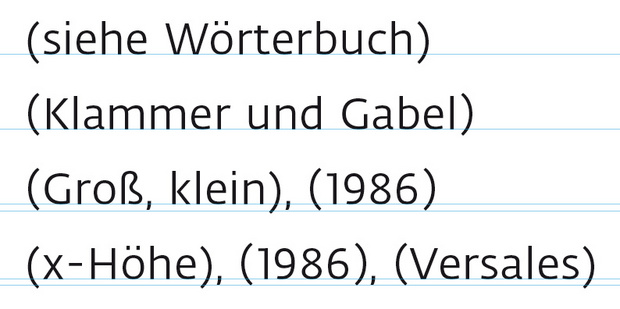
Case Sensitive Klammern bei gemischten Schreibweisen?
beim Setzen eines Textes mit vielen geklammerten Texteinschüben stehe ich vor diesem Problem: case sensitive Klammern bei Versalien zu verwenden ist ein nettes Feature, wenn die Schrift über entsprechende Klammern verfügt, die ihre Form nicht ändern, sondern nur nach oben rutschen (z.B. Fedra Sans). Aber wie setze ich, wenn in kurzen Abständen oder innerhalb einer Klammer gemischte Schreibweisen vorkommen (Zeile 3 und 4, s. Abb.)? Ich tendiere momentan dazu, alle Klammern als Versal-Klammern zu behandeln, wenn sie direkt nebeneinander vorkommen.
Für meine Augen stehen z.B. bei der »(x-Höhe)« die Klammern sowieso optisch etwas zu tief. In diesem Sinn würde ich Dir beistimmen und vermutlich konsequent die Versal-Variante verwenden.
Das ist aber nur meine ganz unprofessionelle Meinung.
Im Bleisatz gibt es nur eine Art Klammer im Setzkasten. Mir ist schon gelegentlich aufgefallen, daß die Klammern mancher Schriften ungünstiger sitzen als andere, aber verändern kann man das in einem Brotschriftgrad nicht, deshalb ist mir diese Problemlösung neu. Wenn du dich im digitalen Satz um dieses Detail kümmerst, korrigiert du dann in einem Text jedes Klammerpaar einzeln? Ist ein solcher Aufwand gerechtfertigt? Bei einem klammerreichen Text steigt doch der Preis für diese Feinkorrektur merklich an, oder?
Bei langen Fließtexten korrigieren ich das nicht, aber bei Briefbögen und Visitenkarten verschiebe ich die Klammern schon einen Hauch nach oben wenn sie zu tief hängen. Das sieht sonst einfach falsch aus, besonders, weil bei Telefon- und Faxnummern nur eine Null in den Klammern steht, die sofort verrät, wenn die Klammern nicht gut sitzen.
Im Bleisatz gibt es nur eine Art Klammer im Setzkasten. Mir ist schon gelegentlich aufgefallen, daß die Klammern mancher Schriften ungünstiger sitzen als andere, aber verändern kann man das in einem Brotschriftgrad nicht, deshalb ist mir diese Problemlösung neu. Wenn du dich im digitalen Satz um dieses Detail kümmerst, korrigiert du dann in einem Text jedes Klammerpaar einzeln? Ist ein solcher Aufwand gerechtfertigt? Bei einem klammerreichen Text steigt doch der Preis für diese Feinkorrektur merklich an, oder?
Dieses Feintuning hängt erst mal von der Schrift ab. Wenn das Verschieben der Klammern einen besseren Satz ergibt, dann macht es bei überschaubaren Text für mich Sinn. Den Aufwand kann man relativ in Grenzen halten, indem man für Klammern ein Zeichenstilvorlage erstellt und dann per Suchen und Ersetzen alle Klammern mit dieser Case Sensitive Funktion belegt. Dann wäre es eine einheitliche Lösung. Daher auch meine Frage, ob man „normale“ oder „höher gestellte“ Klammern mischen kann? Ich finde es eigentlich wichtiger, etwas Luft zwischen dem folgenden oder vorherigen Zeichen und der Klammer zu geben, wenn es zu eng zugeht.
Mich stört es, wenn nebeneinanderstehende Klammern verschiedene Höhen haben. Ich würde im Fließtext einheitlich etwas nach oben gerückte Klammern verwenden; da Oberlängen wesentlich häufiger sind als Unterlängen, wirkt es so auch bei Kleinbuchstaben m.M.n. ausgeglichener.
Ich finde es eigentlich wichtiger, etwas Luft zwischen dem folgenden oder vorherigen Zeichen und der Klammer zu geben, wenn es zu eng zugeht.
Das hat mit der Höhe der Klammern nichts zu tun. Die Schrift sollte so zugerichtet sein, daß die Klammer etwas Fleisch hat. Im Bleisatz habe ich noch nie am Wort klebende Klammern spationieren müssen. (Und das sagt ein denkbar penibler Setzer, der noch mit Seidenpapier in Petit-Schriften ausgleicht, wenn es nötig erscheint.)
Eine unterschiedliche Klammerhöhe darf im Text nicht sichtbar werden, so wären nebeneinanderstehende Klammerpaare in gleicher Höhe zu setzen. Das heißt auch, daß mit Suchen und Ersetzen in einem Werksatz nichts gewonnen ist, weil man den gesamten Text nach jeder Korrektur durchsehen müßte, ob dieses Problem auftritt. Kann man auch mit der Suchfunktion machen, ist aber in meinen Augen überflüssige Liebesmüh, wenn die Schrift selbst eine halbwegs anständige und gut zugerichtete ist. Da stören kleine Akzente den Lesefluß nicht.
Entscheidend ist nicht das Detail in der Regel-Anwendung, sondern der Entwurf nach den weniger genau definierten Regeln der Kunst. Es gibt wenige Autoren, die das einräumen. Man kann es bei Paul Renner lesen: der Satzspiegel sei zwar berechenbar, aber wie er seitlich letztlich auf der Seite steht, kann man nur in einem aufgeschlagenen Blindband festlegen, also nicht allein geometrisch. Auch wenn es inzwischen die Möglichkeit gibt, den Bundschatten digital auf dem Bildschirm zu imitieren, kann man damit noch nicht die Steifigkeit des Papiers und die Art der Bindung so nachahmen wie im körperlichen Buch. In einem fadengehefteten Buch springen die Seiten nach oben, der Satzspiegel wird nach außen gesetzt. In der Klebebindung bleiben sie aufgeschlagen viel leichter liegen, der Satzspiegel kann also weiter nach innen rutschen. Das festzulegen, läßt sich nicht in Berechnung fassen.
Auch das Detail im Schriftsatz wird derzeit überbetont. Gutenberg hat nach unvollkommener Handschrift unvollkommene Lettern geschnitten. Viele Details sind im Bleisatz aus technischen Gegebenheiten unvollkommen geblieben. Das hat den Büchern der berühmten Drucker (Manutius usw.) aber auch ihren Charme verliehen. Die Bedeutung von Regeln im Schriftsatz wird überschätzt. Es ist nicht jedes Detail in eine Regel zu fassen: Ich nenne nur eine irrige Regel des Versalausgleichs, wie sie unterrichtet wird: Gleiche Buchstabenpaare bekommen gleiche Spationierung. Diese Regel verkennt, daß Wörter aus Versalien hellere und dunklere Partien haben (L und U sind in Serifenschriften viel heller als E und B) und der Gesamteindruck einer Zeile durch Anwendung dieser Regel nicht gleichmäßig zu bekommen ist. Wenn dunkle Buchstabenpaare in einem dunklen Wortteil stehen, sind sie diesem anzugleichen. Stehen sie zwischen hellen Buchstaben, sind sie weiter zu sperren. Man wundert sich manchmal sehr, wenn man das gut ausgelichene Wort sieht und dann nachzählt, womit man es harmonisiert hat. Die Regel ist ihrem Ursprung nach falsch. Im Schriftsatz entscheiden nicht die Geometrie, nicht das Rechnen, nicht das Schema, sondern das Sehen. Und das läßt sich nur an meisterlichen Arbeiten schulen, also man muß gute Bücher anschauen.
Ob in Werken die Klammern etwas höher oder tiefer stehen, ist irrelevant. Ein Entwurf muß von enormer Güte sein, wenn er nach Abtötung aller Unregelmäßigkeiten des Schriftsatzes noch lebendig ist. Das gibt es sicherlich, aber ich habe es nur selten gesehen. Mir ist die kleine Ungenauigkeit in einem guten Wurf viel lieber als die auf die Spitze getriebene Präzision in einem langweiligen oder überkandidelten Design.
Die Probleme werden durch den Einsatz von Mediävalziffern insgesamt gemildert und es stört mich deutlich weniger, daß die 3 unten etwas aufsitzt. Das liefert in meinen Augen eher Halt als daß es mich stört. Gemacht wird das in der Praxis aber nun mal einfach nicht.